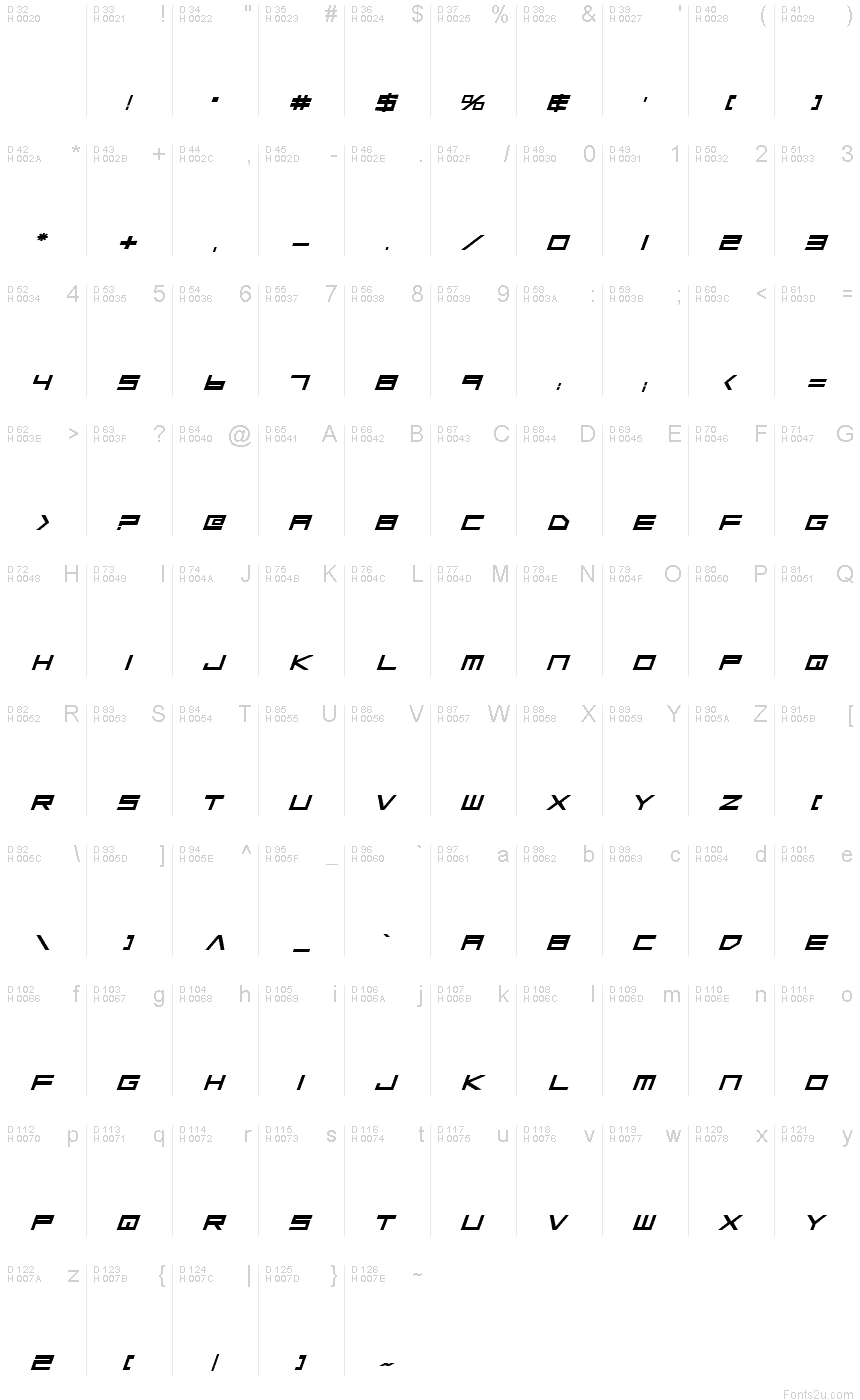
Low Gun Screen Bold ExpItalic, di Iconian Fonts, è un font stencil techno in corsivo gratuito, caratterizzato da lettere larghe, fortemente inclinate e interruzioni strategiche. Il suo ritmo massiccio richiama la velocità e il mondo digitale, mentre gli angoli smussati e le giunture aperte mantengono il design angolare senza risultare pesante.
Questo font gratuito è perfetto per loghi di videogiochi, branding eSport, poster di fantascienza, copertine di musica elettronica, packaging e titoli. Le forme estese conferiscono ai nomi brevi e ai titoli compatti un forte slancio orizzontale, ideale quando la tipografia deve suggerire velocità, meccanica o interfacce digitali.